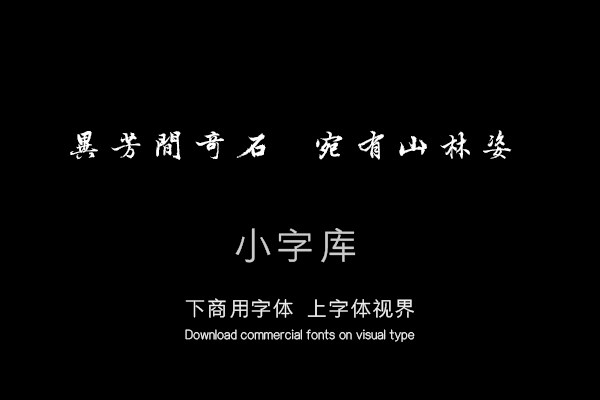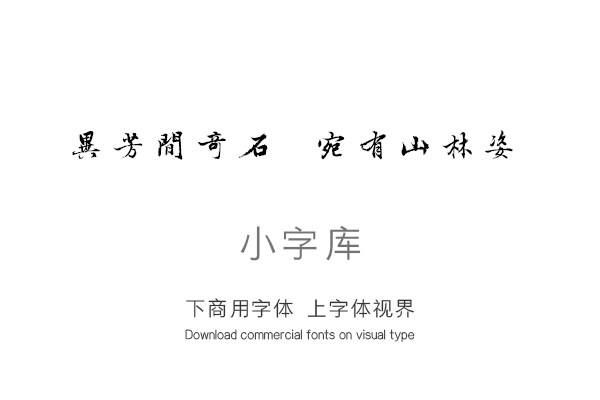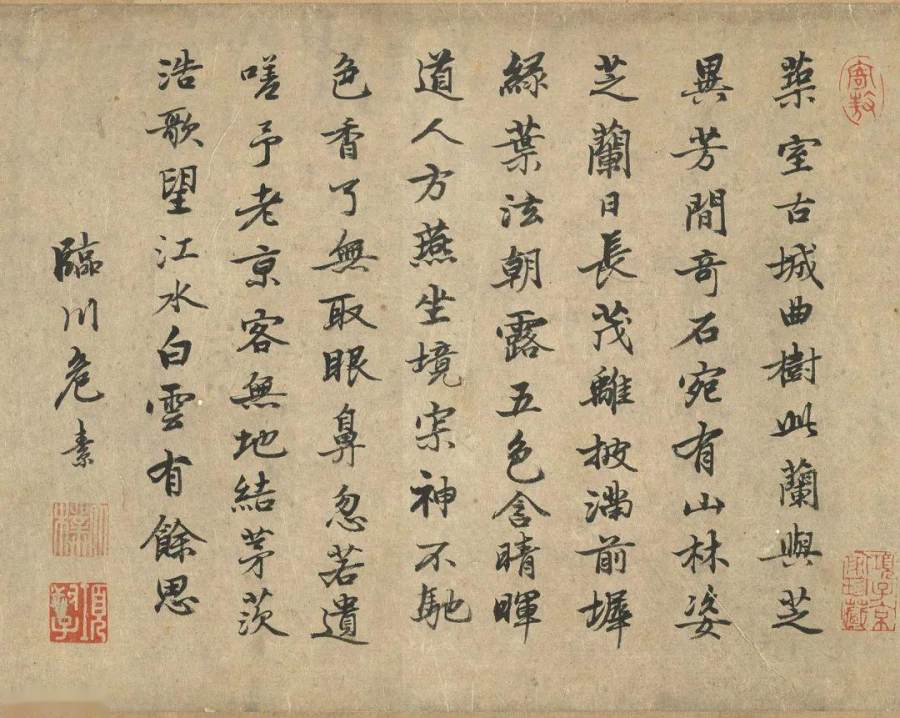
汉标危素行书五言诗
《汉标危素行书五言诗》是一款根据元代危素行书跋芝兰室图五言诗,经过再次调整制作的小字库,该小字库共收录了该真迹作品中约101个字体。
筑室古城曲。树此兰与芝。异芳间奇石。宛有山林姿。芝兰日长茂。离披满前墀。绿叶法朝露。五色含晴晖。道人方燕坐。境寂神不驰。色香了无取。眼鼻忽若遗。嗟予老京客。无地结茅茨。浩歌望江水。白云有余思。临川危素。